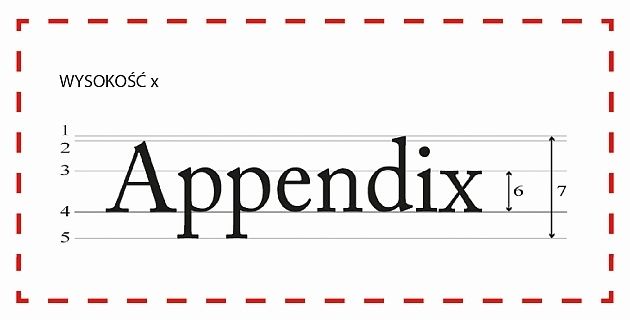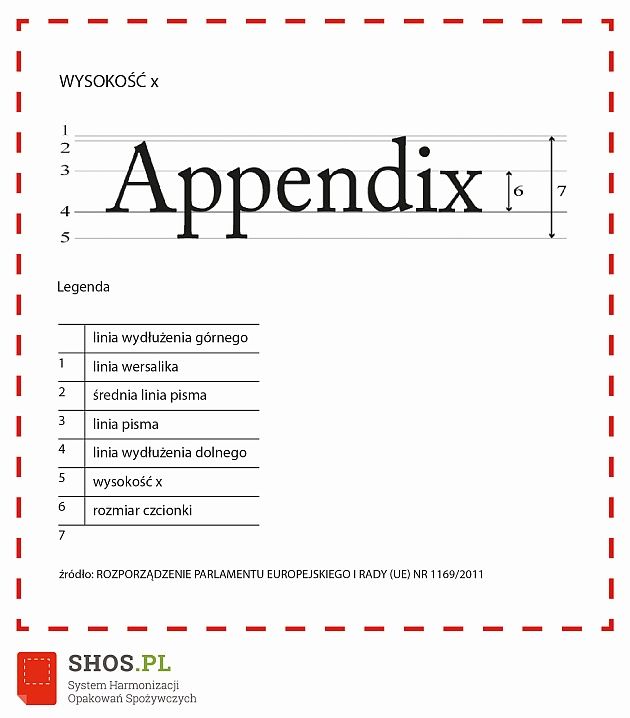
W grudniu ubiegłego roku weszło w życie Rozporządzenie 1169/2011, które wprowadziło nowe wytyczne w temacie projektowania opakowań. Jedną z uwzględnionych wartości, jest minimalny rozmiar czcionki, który ma przyczynić się do lepszego przekazywania konsumentom informacji na temat żywności.
Według nowych regulacji, najmniejsza czcionka powinna mieć rozmiar „x” w wysokości przynajmniej 1,2 mm dla większości opakowań na rynku. W większych opakowaniach z powierzchnią o polu mniejszym niż 80 cm kwadratowych dopuszczalne jest zastosowanie czcionki o „x” w wysokości 0,9 mm. Co ważne, wielkość czcionki nie jest równa jej rozmiarowi wyznaczonemu w punktach, co wprowadza mnóstwo zamieszania.
Źródła, w tym na przykład Food and Drink Industry Ireland, jako minimalną czcionkę (x=1,2 mm) wskazują Times New Roman 8, dla x=0,9 mm odpowiednio Times New Roman 6. Problem pojawia się, gdy chcemy użyć innego fontu, bo czcionki mają rożne wysokości i dlatego rozmiaru 8 nie powinniśmy traktować jako uniwersalny - radzi Alicja Sidorowicz, koordynator SHOS.PL, projektu zajmującego się weryfikacją opakowań spożywczych pod kątem Rozporządzenia 1169/2011.
Dodajmy, że 1,2 mm to wysokość „x”, czyli wysokość liter, takich jak a, c, x, z czy choćby u. Określenie ich wysokości wpływa na pozostałe litery, których wysokość ustalana jest automatycznie. Problem może jednak zaistnieć, gdy trzeba określić wysokość wersalików. Jak podaje przewodnik po Rozporządzeniu wydany przez IJHRS: w przypadku liter drukowanych i cyfr należy stosować wielkość czcionki jak dla litery „A” w wyrazie „Appendix” podanym jako przykład w Załączniku IV rozporządzenia.
Rozporządzenie 1169/2011 definiuje wysokość czcionki, którą zapisane będą obowiązkowe informacje na temat żywności. Wysokość ta, to „x” = 1,2 mm. Dopuszczalne są jednak wyjątki, które łatwo jest przeliczyć w stosunku do powierzchni opakowania, jeśli to ma kształt prostopadłościanu. Problemy zaczynają się w przypadku opakowań o nieregularnym kształcie.
Jeżeli mamy do czynienia z bardziej skomplikowanymi kształtami opakowań (cylindrycznymi, nietypowymi) za największe pole powierzchni, według najnowszych wytycznych, należy uznać 1/3 jego powierzchni bocznej objętej jednym polem widzenia, bez wieczek, denek i nakrętek - tłumaczy Alicja Sidorowicz. Dodajmy jednak, że wszelkie wyliczenia dotyczą tylko powierzchni, które nadają się na zadruku.
Rozporządzenie rozpisane zostało cztery lata temu, a w życie weszło w zeszłym roku. Ciągle jednak część opakowań nie została dostosowana do nowych wytycznych, a wśród tych zaprojektowanych od nowa zdarzają się błędy. Dlaczego warto przyłożyć się do poprawnego i czytelnego zaprojektowania opakowań pod względem czcionki?
Otóż wielkość czcionki jest dla konsumenta jedną z najważniejszych zmian, wprowadzonych przez przytaczane Rozporządzenie. Celem zmiany jest umożliwienie konsumentom podejmowania racjonalnych decyzji zakupowych oraz, osobom z problemami ze wzrokiem, sprawdzania składników danych produktów bez konieczności sięgania po lupę.